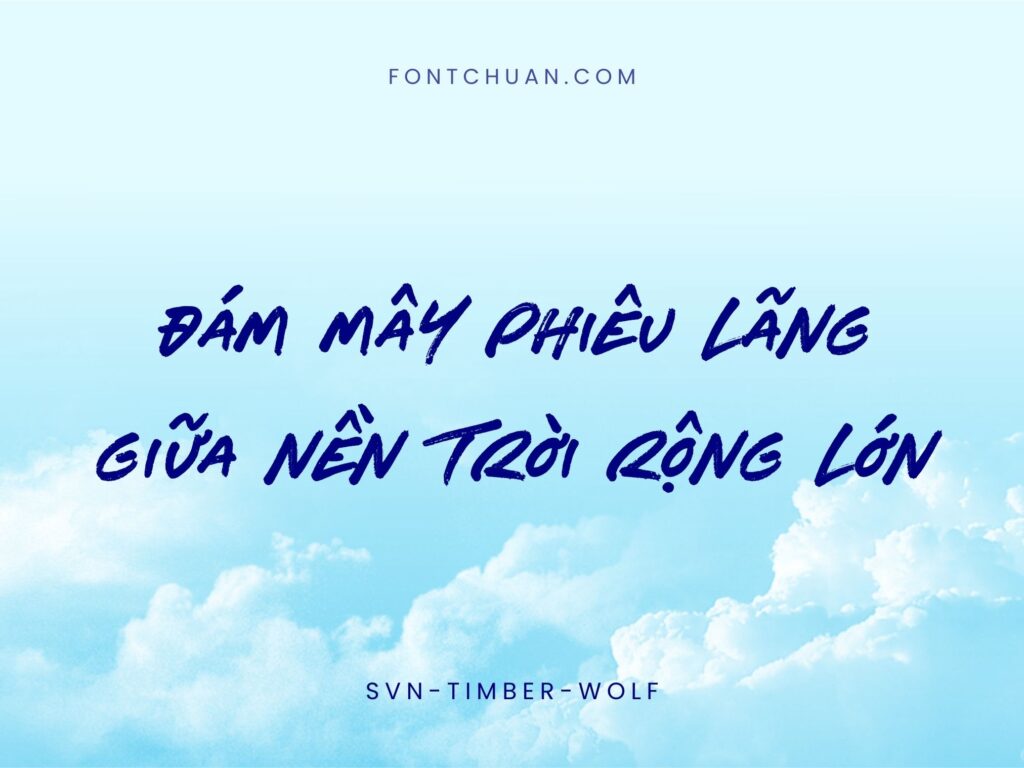
Font SVN Timber Wolf Việt Hóa
Tác giả Font: Greg Nicholls
Font SVN Timber Wolf là phiên bản Việt hóa của kiểu chữ Timber Wolf, được thực hiện bởi STYLEno.1 Fonts. Timber Wolf là một font chữ viết tay siêu thực, được thiết kế bởi Greg Nicholls và phát hành bởi Rook Design Supply. Font này sử dụng công nghệ OpenType-SVG mới nhất, cho phép tái tạo chính xác các đường nét và kết cấu của chữ viết tay thực sự. Timber Wolf bao gồm cả phiên bản SVG và phiên bản vector hóa (OTF/TTF), phù hợp cho nhiều mục đích sử dụng như thiết kế logo, tiêu đề, bao bì sản phẩm và các ấn phẩm quảng cáo.
SVN Timber Wolf lý tưởng cho các dự án thiết kế yêu cầu sự chân thực và sáng tạo, như thiết kế logo, tiêu đề, bao bì sản phẩm và các ấn phẩm truyền thông. Các ngành nghề như quảng cáo, ẩm thực và spa có thể tận dụng font này để tạo điểm nhấn trong thiết kế. Ngoài ra, font cũng thích hợp cho các sự kiện như Tết, Giáng sinh, Valentine và các lễ hội khác.